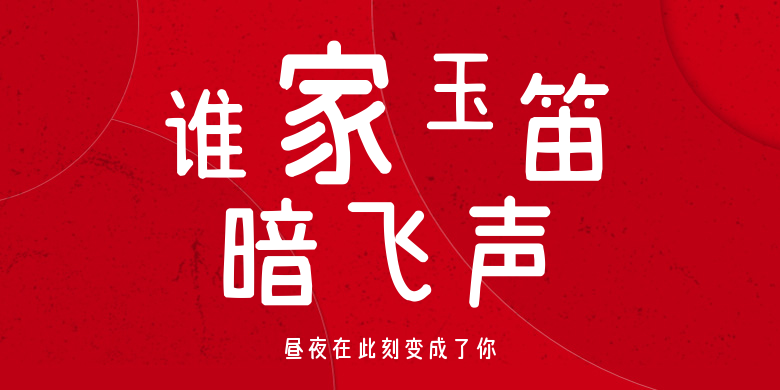
昼夜在此刻变成了你
昼夜在此刻变成了你,这款字体结构工整、笔画清晰,兼顾美观与易读性,适用于标题、正文、海报、包装、LOGO 等多种场景。字形优雅稳定,风格百搭耐看,适配日常排版与创意设计,让文字呈现更舒适、更具质感。昼夜在此刻变成了你一笔一画,皆是细节,以均衡的比例、流畅的线条打造舒适视觉体验,字形端正大气,风格简约现代。无论是商业设计、品牌宣传还是日常排版,都能轻松驾驭,让文字更有格调与力量。昼夜在此刻变成了你字体下载。